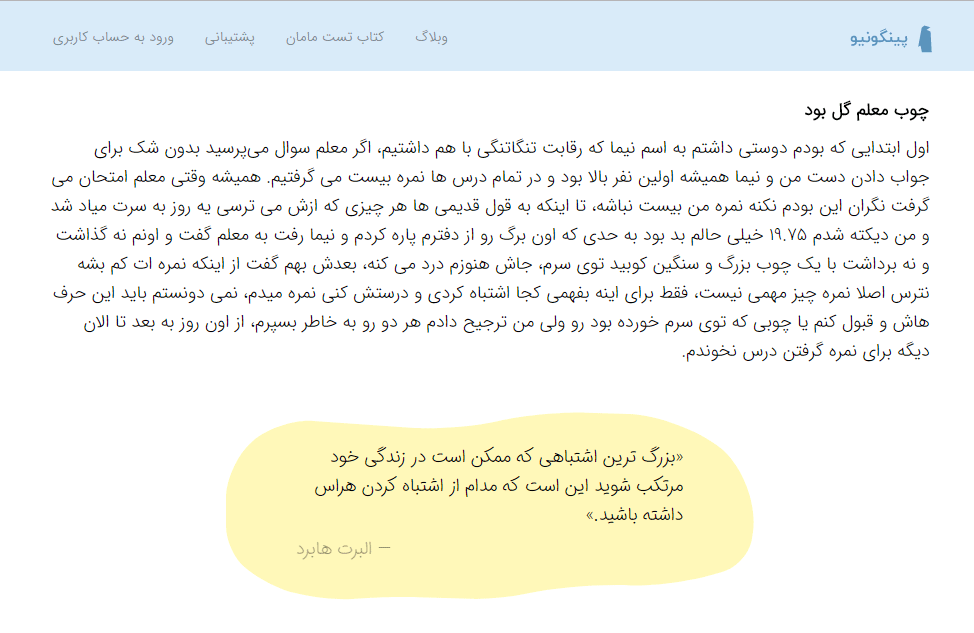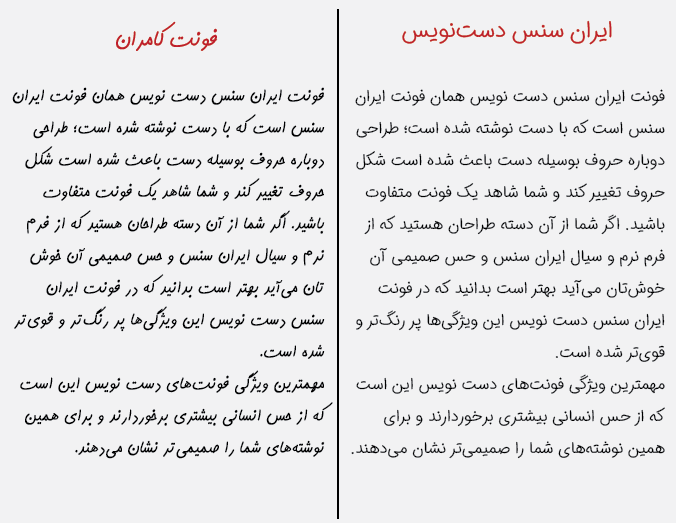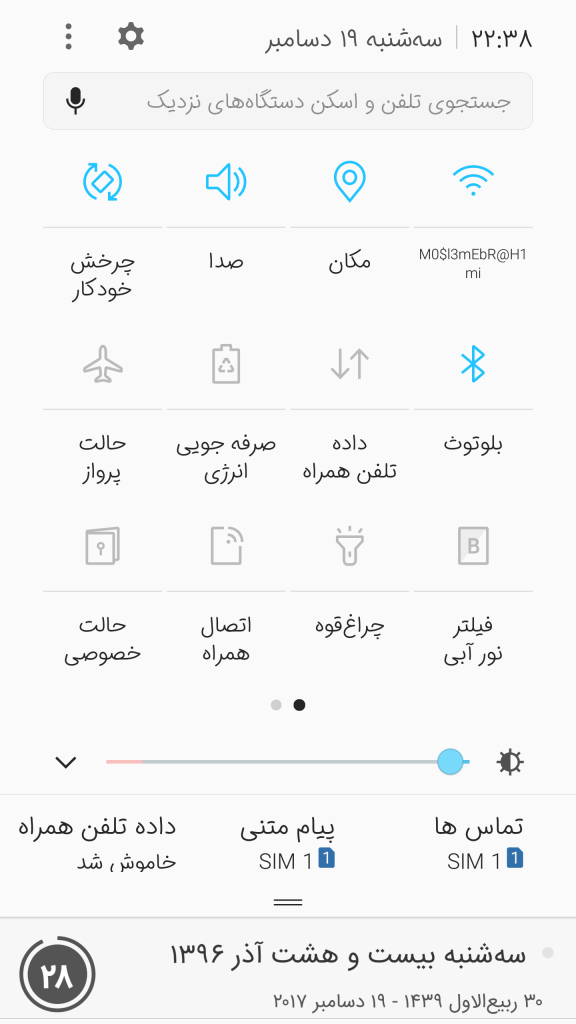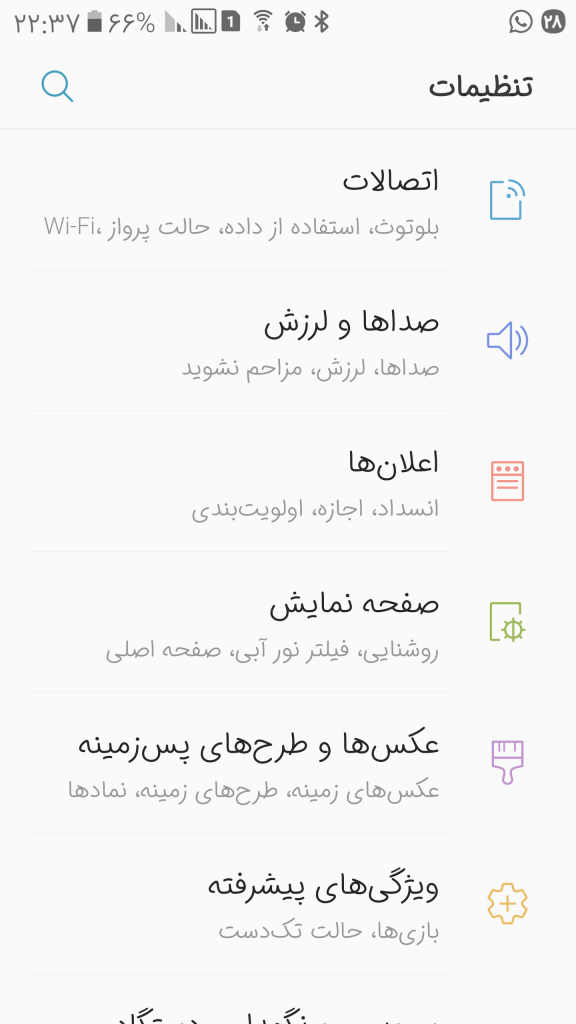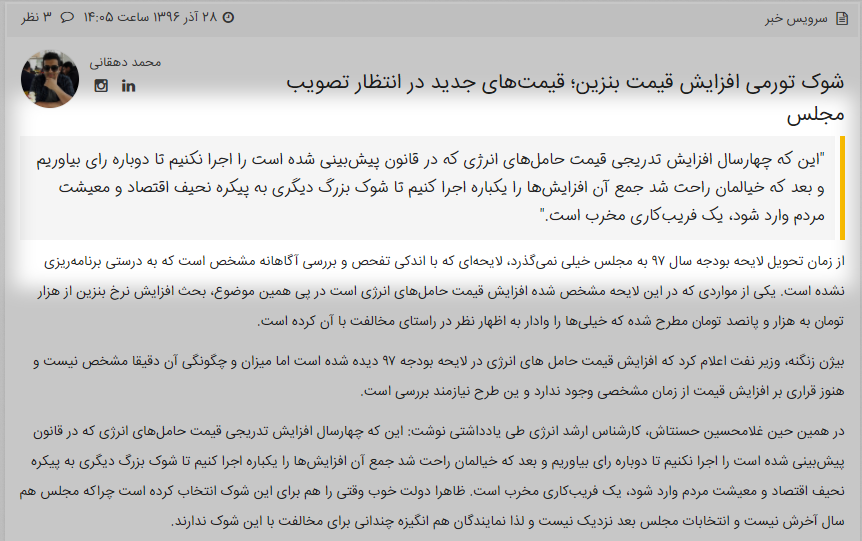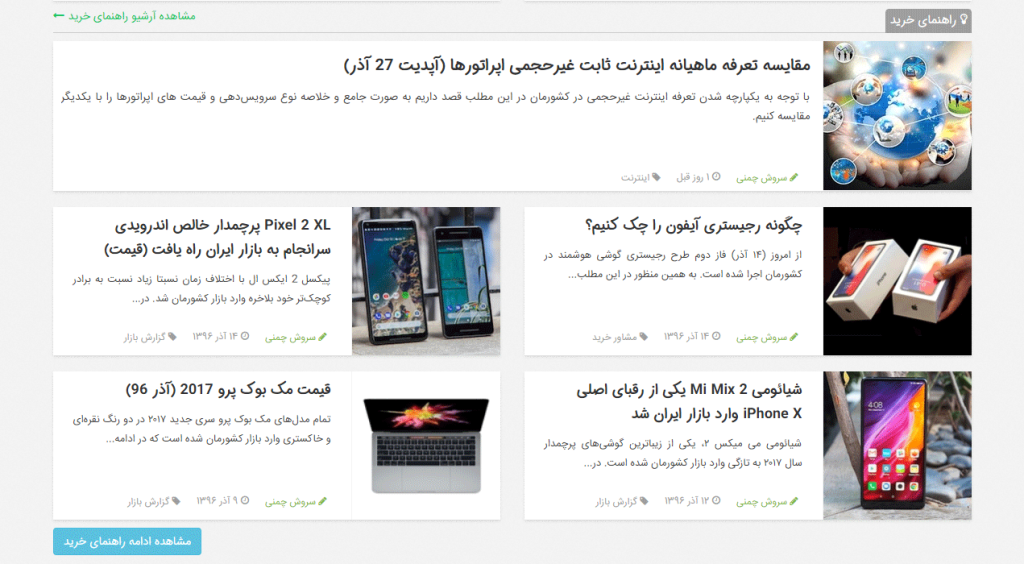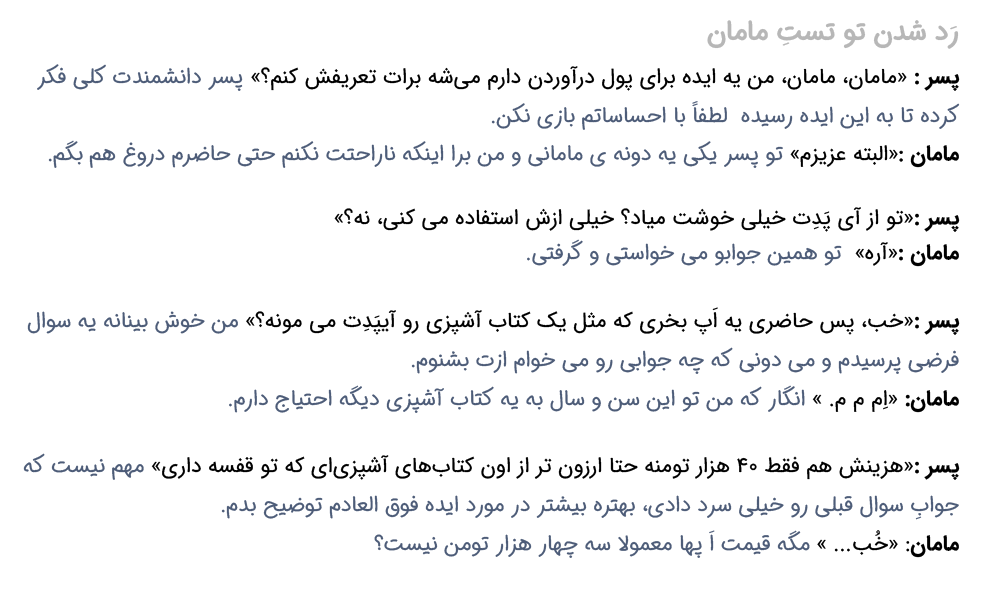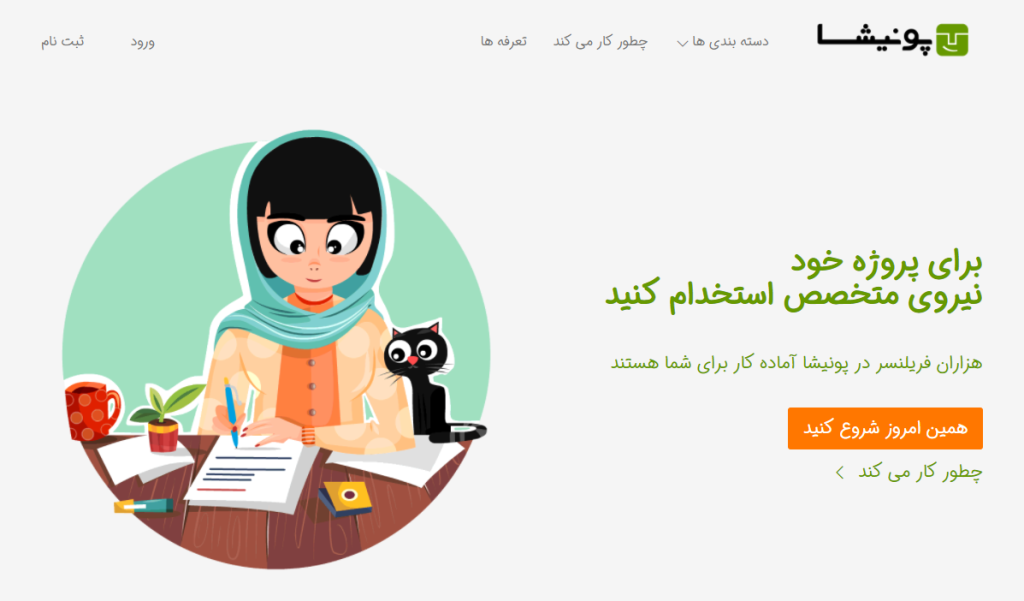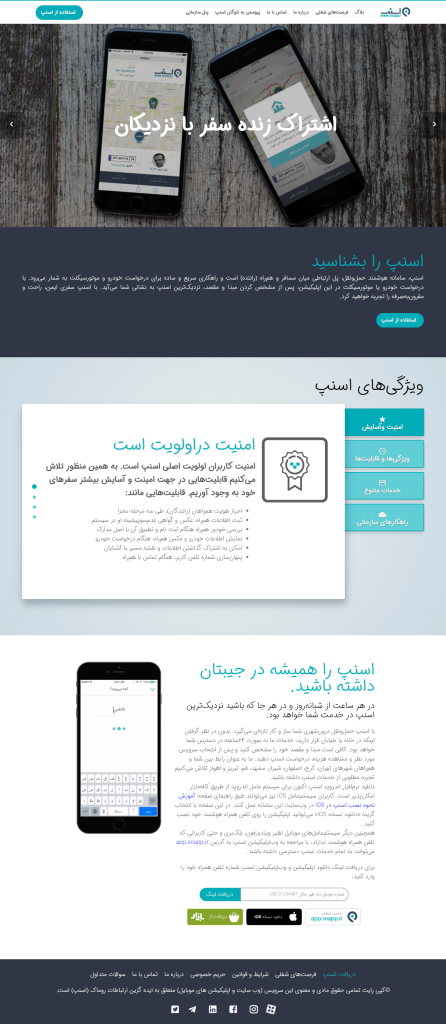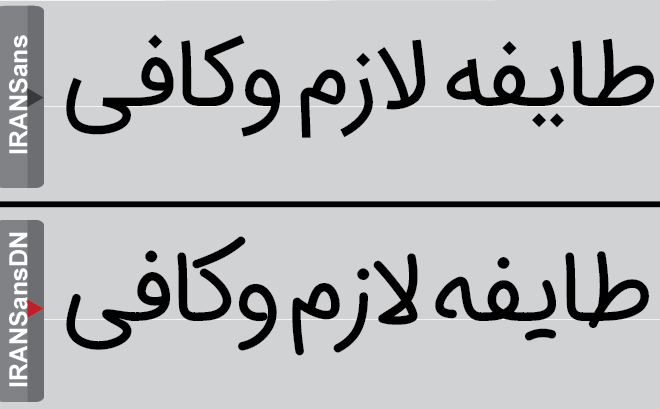
فونت ایران سنس دست نویس توسط طراح و خالق تایپ فیس مشهورایران سنس و فونت ایران ساخته و طراحی گردیده است. با ما همراه باشید تا این قلم زیبا که ارتباطی صمیمی با مخاطبین خود برقار می کند را به شما معرفی کنیم.
فونت ایران سنس دست نویس
فونت ایران سنس دست نویس نسخه بازطراحی شده با قلم و استایل گرد تایپ فیس مشهور ایران سنس است. اما با تفاوت های زیادی که نسبت به نسخه تایپ شده توسط عنصرماشین خود دارد. به واقع قلمی منحصر به فرد را در نوع و سبک خود رقم زده است. همان طور که از نام این تایپ فیس پیداست از خانواده دست نویس است.
با کمی دقت در فرم های حروف در این قلم که در تصاویر نمونه زیر نیز آمده است. کاملا مشخص است که بسیاری از حروف نسبت به نسخ ایران سنس کاملا متفاوت طراحی گردیده . می توایند در تصاویر زیر این تفاوت و منحصر بودن و متکی بودن به سبک دورنی خود را مشاهده نمائید. بسیاری از طراحان و علاقه مندان به تایپوگرافی تمایل به استفاده از فونت هایی با فرم های نرم و روان و سیال اند. این ویژگی های مذکور در این تایپ فیس بسیار پر رنگ و قوی می باشد.
یکی از مهمترین ویژگی های خانواده دست نویس دارا بودن عنصر و درون مایه انسانی می باشد. به سبب طراحی فرم های حروف و ترکیبات با دست انسان، ارتباط صمیمی و گرمی را با بیننده و مخاطب خود برقرار می نماید. بدون شک حس دیدن و خواندن متنی که توسط دست آدمی نوشته شده است بسیار متفاوت تر از نگارشی است که به وسیله فونت های ماشینی انجام گردیده است.
از این جهت کاربرد و حوزه استفاده از فونت های دست نویس هم متفاوت از تایپ فیس های طراحی شده توسط عنصر ماشین می باشد. از قلم ایران سنس دست نویس می توانید برای انواع متون ریز و طولانی و یا عناوین و تیترهای جذاب و تبلیغاتی برای موضوعات محاوره ای و غیر رسمی، کودک و نوجوان کارتون ها جشنواره ها فیلم نامه ها بیلبورد ها و … چه در محیط نشر و چاپ و چه فضای وب و دیجیتال بهره مند شوید.
تایپ فیس ایران سنس همانطور که همه می دانند از مشهورترین و پرکاربرد ترین قلم ها در تایپوگرافی فارسی می باشد که بسیاری از نشریات و وب سایت ها و استارت آپ های ایرانی از آن استفاده می کنند. شما می توانید با بهره بردن از نسخه دست نویس این قلم که تفاوت های زیادی با نسخه اصلی آن دارد. برای جذاب تر کردن طراحی ها و نوشته های خود استفاده لازم را ببرید. چرا که دارای شخصیتی مهربان و صمیمی است و مکملی زیبا برای نسخه اصلی می باشد.
در زیر تصاویری نمونه از این تایپ فیس زیبا برای شما عزیزان قرار داده شده است. در تصاویر زیر می توانید نوع فرم ها و تفاوت های آن با نسخه اصلی را مشاهده کنید.
3 وزن
این ۳وزن هماهنگی دقیقی با یکدیگر و با فونت‌های لاتین هم وزن خود دارند.
فونت ایران سنس دست نویس
همانطور که می دانید مهمترین ویژگی فونت‌های دست نویس برخورداری بیشتر از حس انسانی بیشتری برخوردار هستند و به همین سبب نوشته‌های شما را صمیمی‌تر نمایان می سازند.
بی شک حس دیدن و خواندن یک دست خط برای شما متفاوت از متنی است که به‌وسیله فونت تایپ شده است.
فونت‌های ماشینی هرگز نمی‌تواند این ادراک انسانی را منتقل کند اما به هر صورت ما روز به روز بیشتر وابسته تکنولوژی شدیم و به همین سرعت کمتر از قلم و کاغذ برای نوشتن استفاده کردیم. تا جایی که حتی نوشته‌های غیر رسمی و شخصی‌‌امان را نیز با فونت تایپ کردیم. فونت‌های سبک دست‌نویس برای جبران این کمبود طراحی می‌شوند و به همین دلایل نیز طرفداران زیادی دارند.